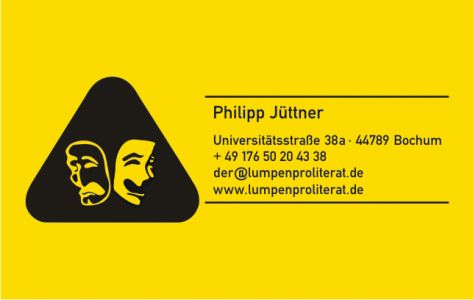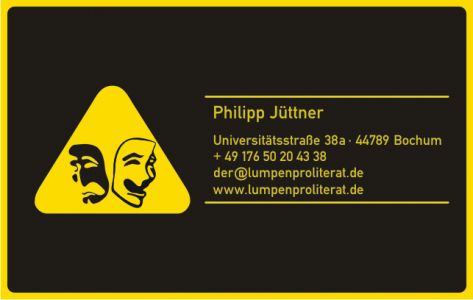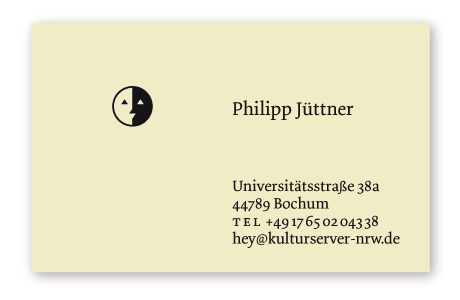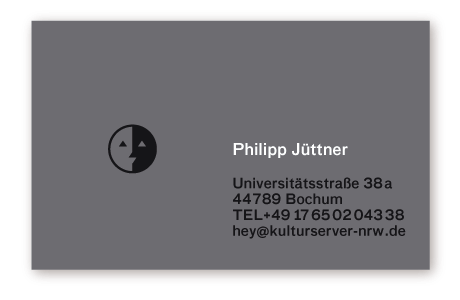
da heute die sonne so schön scheint habe ich auf die schnelle was gemacht, wie findest du es?
auf der visitenkarten fehlt mir irgendeine angaben zum
tätigkeitsbereich. nur die masken sagen mir noch zu wenig ...
auf der visitenkarten fehlt mir irgendeine angaben zum
tätigkeitsbereich. nur die masken sagen mir noch zu wenig ...
Vielleicht will sich Herr Jüttner da ja gar nicht so genau festlegen? :wink:
hier ein paar vorschläge:
1. versuche das logo kleiner zu gestalten, das ist momentan
viel zu heft, schau dir das beispiel von typografski an, dezent
ist besser.
2.
ggf. solltest du das logo überarbeiten. ich gehe richtig in der
annahme das du ein ambigramm haben möchtest, oder?
das logo soll durch eine 180° drehung immernoch lesbar sein?
dann würde ich dir empfehlen a und b in der höhe anzugleichen,
ggf noch etwas an den rundungen und an der strichstärke arbeiten.
3.
die vertikale linie am adressblock ist quatsch. das ist doppelt gemoppelt.
du hast bereits 2 horizontale trennungen. eine durch die farbliche
teilung und eine durch die linksbündigkeit (gibts das wort?) des
adressblocks.
4.
tabs. tabulatortaste das ist die über der großen shifttaste, drück die mal.
schau an was passiert, die zeile springt an einen festen platz und
siesen kann man sogar variieren. einfach genial, wer sich sowas ausdenkt.
ich denke das ist eine so gute erfindung, die solltest du bei den telefon-
nummer anwenden. dann kannst du auch diese doppelpunkte streichen.
5.
telefonnummern richtig trennen. http://de.wikipedia.org/wiki/DIN_5008
030 1234567. mach diese sinnlosen striche raus. entweder klammern
oder nichts. von hinten in 2er-schritten abteilen würde ich nur wenn es
logisch erscheint, also bei rufnummern wie 56 56 58 oder so.
6. versuch mal eine farbliche 50/50 teilung, direkt in der mitte wie das
aussieht. ich finde es so irgendwie quatsch. ist natürlich der eigene
geschmack der hier zählt aber auch ein hochformat könnte ich mir
gut vorstellen.
soviel erstmal dazu, nix für ungut. 8)
@ hey, die proportionen bei deinen entwürfen sind etwas holprig, die farben auch so naja.
da heute die sonne so schön scheint habe ich auf die schnelle was gemacht,
wie findest du es?
die schriften sind:
1. DOLLY
2. FF BAU
Vielen Dank für Deine Mühe. In Sachen Proportion geb ich Dir recht. Die Hintergrundfarben stehen nur Stellvertretend für einen schönen Karton, der noch auszusuchen wäre. Den gelben Entwurf hab ich mal ausgehend von der in diesem Thread früher zu lesendenden Erklärung, im Visitenkartenbuch nicht überblättert zu werden wäre ebenso wichtig wie eine schöne Gestaltung, gemacht.
Ich mag Deinen Entwurf, find Ihn ehrlich sehr schön. Die Dolly ist wunderschön, die FFBau scheint mir nicht zu mir zu passen, zu technisch (die DIN hab ich auch nur des Warnschild-Looks wegen benutzt). Trotzdem, in diese Richtung kann ich nicht gehn. Ähnliche Gestaltungen wurden im Theaterumfeld der 60er Jahre gern benutzt (ein Theaterverlag hat auch noch heute ein ganz ähnliches Logo) und Leute aus meinem Fach würden möglicherweise Dinge Assoziieren, die ich ganz und gar nicht vertreten will.
auf der visitenkarten fehlt mir irgendeine angaben zum
tätigkeitsbereich. nur die masken sagen mir noch zu wenig ...
Vielleicht will sich Herr Jüttner da ja gar nicht so genau festlegen? :wink:
Ganz genau, jede genauere Festlegung wäre zwangsläufig falsch und ein Bündel sieben halbgarer Bezeichnungen will ich da auch nicht stehen haben.
ich finde die idee mit dem gelben warnschild super.
es knallt rein, es wirkt mehr oder weniger lustig, vorallem
eregt es aufsehen – eine lachende und eine weinende
gasmaske vielleicht? hehehe.
wenn du die masken vom stil her dem schild noch anpasst,
und hier und da noch etwas an der typo arbeitest, könnte die
karte gut aussehen.
Ganz genau, jede genauere Festlegung wäre zwangsläufig falsch und ein Bündel sieben halbgarer Bezeichnungen will ich da auch nicht stehen haben.
problem ist, dass ich deiner karte nicht entnehmen kann
ob du maskenbildner, theaterkritiker, puppenspieler oder
schriftsteller bist. vielleicht hast du ja auch nur ein dauer-abo
fürs lokale theater besitzt.
sich nicht festlegen ist eine sache - aber ein paar infos hätte
ich als potientieller kunde schon ganz gern. wie du dein
arbeitsgebiet definiert ist dir überlassen - momentan weiss
ich aber nichtmal ob du arbeitest oder es sich um eine rein
private karte handelt.
8)
Ganz genau, jede genauere Festlegung wäre zwangsläufig falsch und ein Bündel sieben halbgarer Bezeichnungen will ich da auch nicht stehen haben.
problem ist, dass ich deiner karte nicht entnehmen kann
ob du maskenbildner, theaterkritiker, puppenspieler oder
schriftsteller bist. vielleicht hast du ja auch nur ein dauer-abo
fürs lokale theater besitzt.
sich nicht festlegen ist eine sache - aber ein paar infos hätte
ich als potientieller kunde schon ganz gern. wie du dein
arbeitsgebiet definiert ist dir überlassen - momentan weiss
ich aber nichtmal ob du arbeitest oder es sich um eine rein
private karte handelt.
8)
Es geht aber im meinem Fall nicht um potentielle Kunden, sondern um Partner für künstlerische Projekte. Die können meinen Tätigkeitsbereich in der Regel aus eigener Erfahrung gut einschätzen. Auftragskunst und damit Kunden im Theaterbereich gibt es durchaus – aber diese Kunden brauchen dann einje spezielle Ansprache, da wäre es mit meiner Visitenkarte ohnehin nicht getan. Zudem arbeite ich augenblicklich nicht in dem Bereich.
Ich bin dankbar für die vielen Anregungen bisher und ich werd mich sicher noch intensiver mit ihnen Auseinandersetzen. heute und gestern kam etwas dazwischen, darum gibt es einstweilen nur einen Zwischenstand zu sehen. Andere Maskenvarianten folgen sicher noch. Ich habe hier ein wenig weiter am Warnschild-Entwurf geschraubt, mit leicht vereinfachten Masken:
1096_visic_1.jpg
1096_visid_1.jpg
1096_visie_1.jpg
Also ich finde die Kombination der DIN, des Verkehrsgelbes und
des Warndreiecks etwas zu sehr in Richtung: ACHTUNG ... oder?
Schon, aber genau das war ja die Idee. Ich denke, da ich sonst branchenunüblich eher bescheiden Auftrete, könnte ich mir das schon erlauben, ohne negativ aufzufallen.
Ganz genau, jede genauere Festlegung wäre zwangsläufig falsch und ein Bündel sieben halbgarer Bezeichnungen will ich da auch nicht stehen haben.
problem ist, dass ich deiner karte nicht entnehmen kann
ob du maskenbildner, theaterkritiker, puppenspieler oder
schriftsteller bist. vielleicht hast du ja auch nur ein dauer-abo
fürs lokale theater besitzt.
sich nicht festlegen ist eine sache - aber ein paar infos hätte
ich als potientieller kunde schon ganz gern. wie du dein
arbeitsgebiet definiert ist dir überlassen - momentan weiss
ich aber nichtmal ob du arbeitest oder es sich um eine rein
private karte handelt.
8)
Und ich dachte, das Logo wäre mehr (lebens-)philosophisch gemeint.
So Yin & Yang mäßig.
Ich bin dankbar für die vielen Anregungen bisher und ich werd mich sicher noch intensiver mit ihnen Auseinandersetzen. heute und gestern kam etwas dazwischen, darum gibt es einstweilen nur einen Zwischenstand zu sehen. Andere Maskenvarianten folgen sicher noch. Ich habe hier ein wenig weiter am Warnschild-Entwurf geschraubt, mit leicht vereinfachten Masken:
1096_visie_1.jpg
Die hier gefällt mir gut.
Sie ist nicht aufdringlich, hat Stil.
Ich bin dankbar für die vielen Anregungen bisher und ich werd mich sicher noch intensiver mit ihnen Auseinandersetzen. heute und gestern kam etwas dazwischen, darum gibt es einstweilen nur einen Zwischenstand zu sehen. Andere Maskenvarianten folgen sicher noch. Ich habe hier ein wenig weiter am Warnschild-Entwurf geschraubt, mit leicht vereinfachten Masken:
1096_visie_1.jpg
Die hier gefällt mir gut.
Sie ist nicht aufdringlich, hat Stil.
Für mich hat das was genormtes, hoheitliches, autoritäres. Kann ich alles in der Kultur nicht so recht gebrauchen.751_2121403_1.jpg
... sehe ich ähnlich: die Verbindung Kultur und Gefahrenschild leuchtet mir auch nicht sofort ein. Die lachende/weinende Maske ist eher ein "Theaterzeichen" und zudem ein recht oft Bemühtes. Da gibt es sicherlich etwas Originelleres? Vielleicht eine als Bühne gestaltetes Visitenkarte, so mit Vorhang ... und die Daten, wie eine Art Kinoabspann, so mit Punktlinien dazwischen? Doch das wär wahrscheinlich schon wieder etwas zu viel Impression, keine Ahnung! Kommt freilich wieder sehr auf die Leutchen an, insofern wird es der Philipp sicher besser wissen.
So, wieder im Lande und holla: brauchte eine halbe Stunde, um das alles zu lesen und den Anschluss zu finden => Respekt!
Der Entwurf der "Übungskarte" von Microboy gefällt mir übrigens auch am besten.
Gerade die Verbindung Theater <> Gefahrgut finde ich gut.
Hier muß man sich frage, was Theater heute denn bedeutet? Vom eigenen Anspruch her doch weit mehr als nur eine Wiedergabe des ursprünglichen Manuskriptes. Es ist und war doch immer gerade auch Inspiration, Auslegung, Interpretation.
Und daß bei einer solchen die Gemüter des Bürgertums (also einer der Hauptzielgruppen des Theaters) ins Wallen kommen, ist nicht nur heute so. "Skandalvorstellung" verriß man schon Berthold Brecht-Stücke oder die vom Schweinehund Arnolt Bronnen:
http://de.wikipedia.org/wiki/Arnolt_Bronnen
Theater muß sich doch als Avantgarde verstehen, wider den Zeitgeist und für den revolutionären künstlerischen Aufbruch.
Was sonst symbolisiert Theater also besser als eine Anspielung auf Gefahrgut?
:shock: Verdrehte Welt: Ich bemühe die Tradition und Bleisetzt auf Avantgarde! :lol: Was folgt als Nächstes: TYPOGRAFSKI verwendet eine Garamond? :P
Vielleicht siehst Du einfach den Bleisetzer falsch? :D
Aber ich meinte das ganz ernst. So sehe ich Theater.
Auch, wenn ich mit dem heutigen und dessen Interpretationen oftmals nicht klarkomme, wahrscheinlich, weil ich es nicht verstehe.
Aber schau' Dir Bert Brecht an. Für unsere Nachkriegsgeneration im Westen war doch oftmals nur Pflichtlektüre an der Schule, wie Lenz, Handke, Fritsch. In den 1920er Jahren war Brecht für viele der TEUFEL. Seine Stücke stellten aus damaliger Sicht alles in Frage, was dem Bürgertum heilig war. Der war in deren Augen reiner Sprengstoff.
Vor einigen Monaten diskutierte ich mit einem Buchdruck-Freund und Bühnenleiter eines Staatstheaters über Bronnen (den ich verachte) und Brecht (den ich verehre). Brecht hatte bei ihm keinen hohen Stellenwert mehr. Sei aus-interpretiert. Das mag sein. Aber auch heute gibt es solche Attentäter, die ihren Sprengstoff dem Bürgertum unter die Couch-Garnitur werfen: Schlingensief (den ich nicht mag), Fassbender (den ich sehr mag), dessen Stück über die Frankfurter Spekulations-Immobilien zum Skandal wurde, weil er angeblich antisemitische Tendenzen aufweise.
Ich meine, eine solche Visitenkarte steht in sehr guter Tradition.